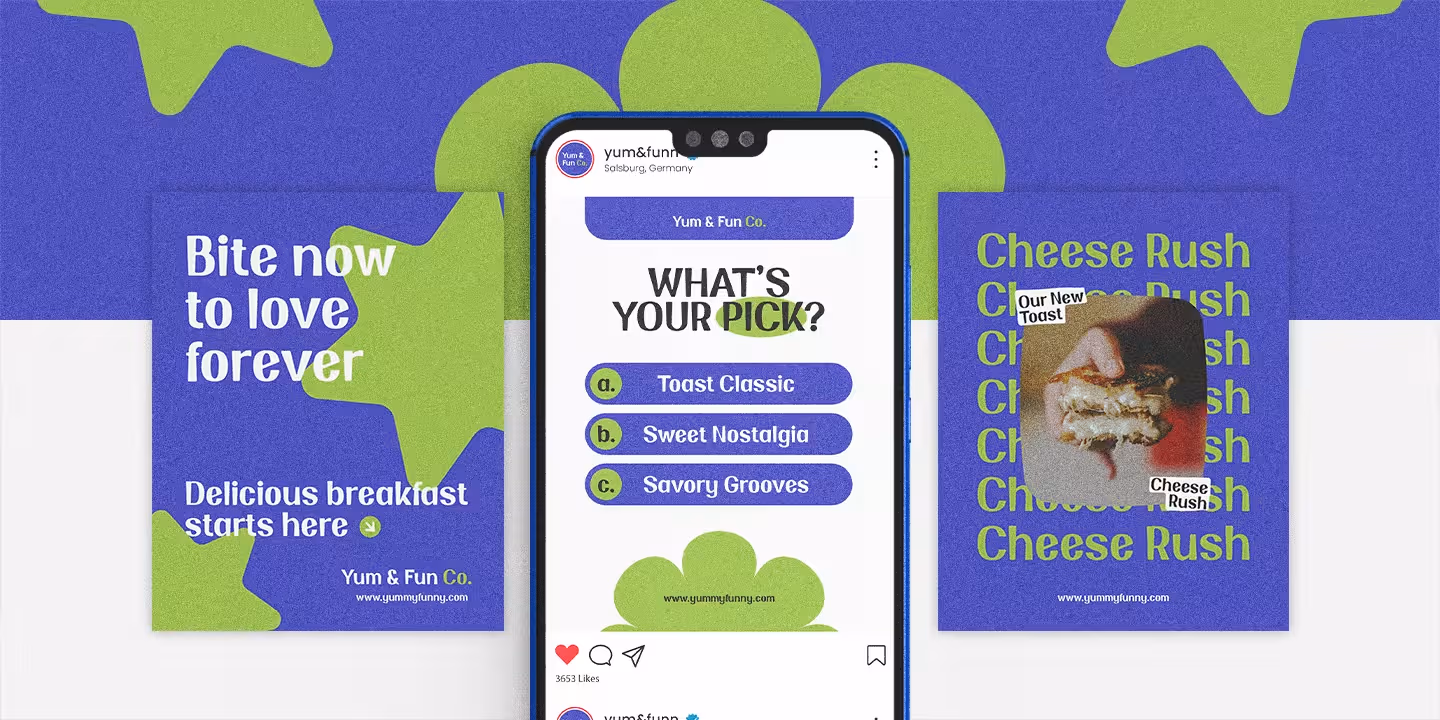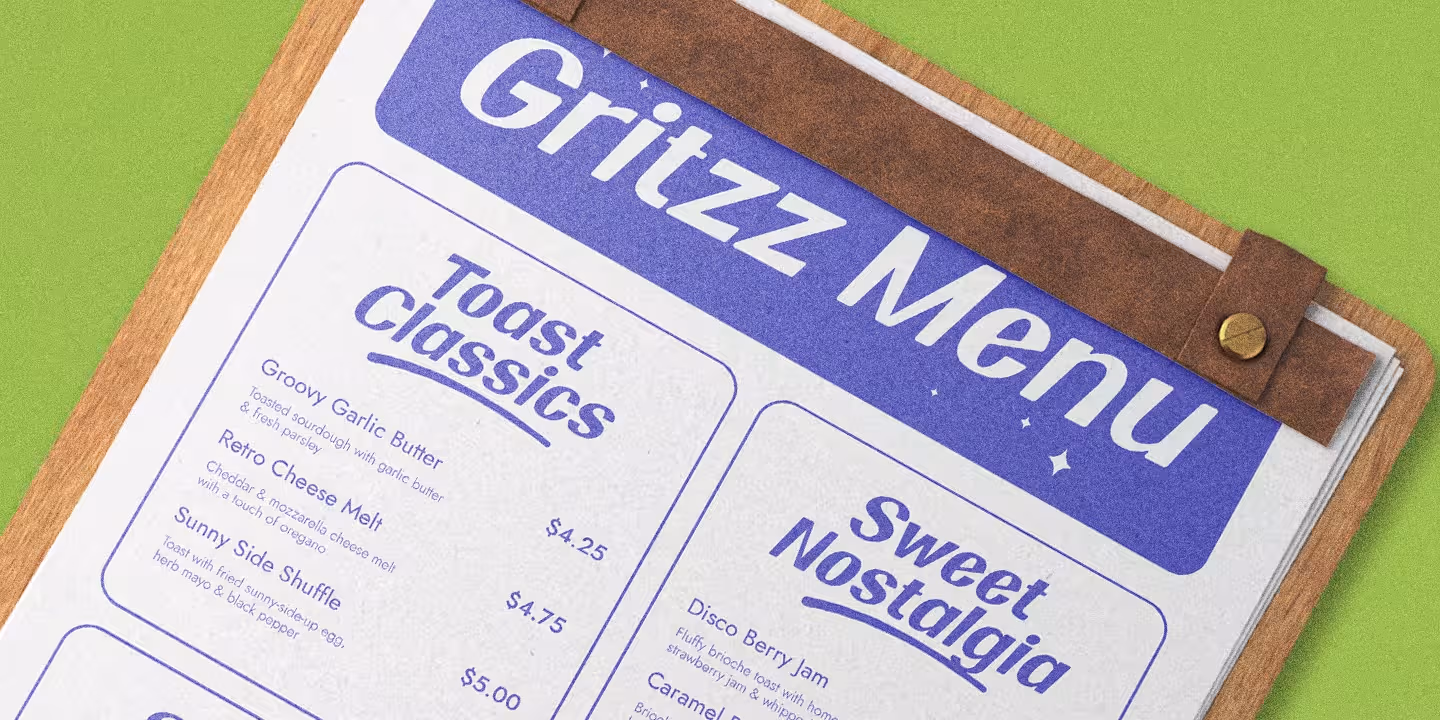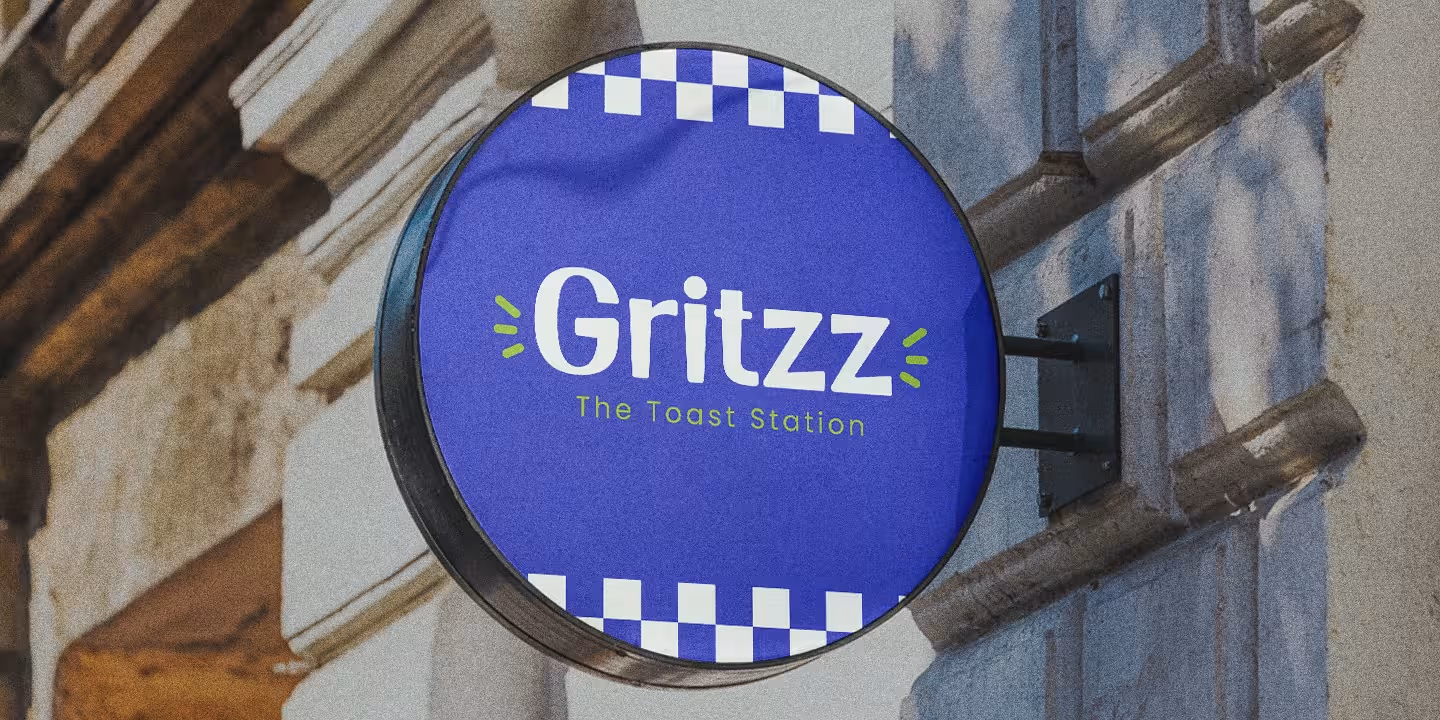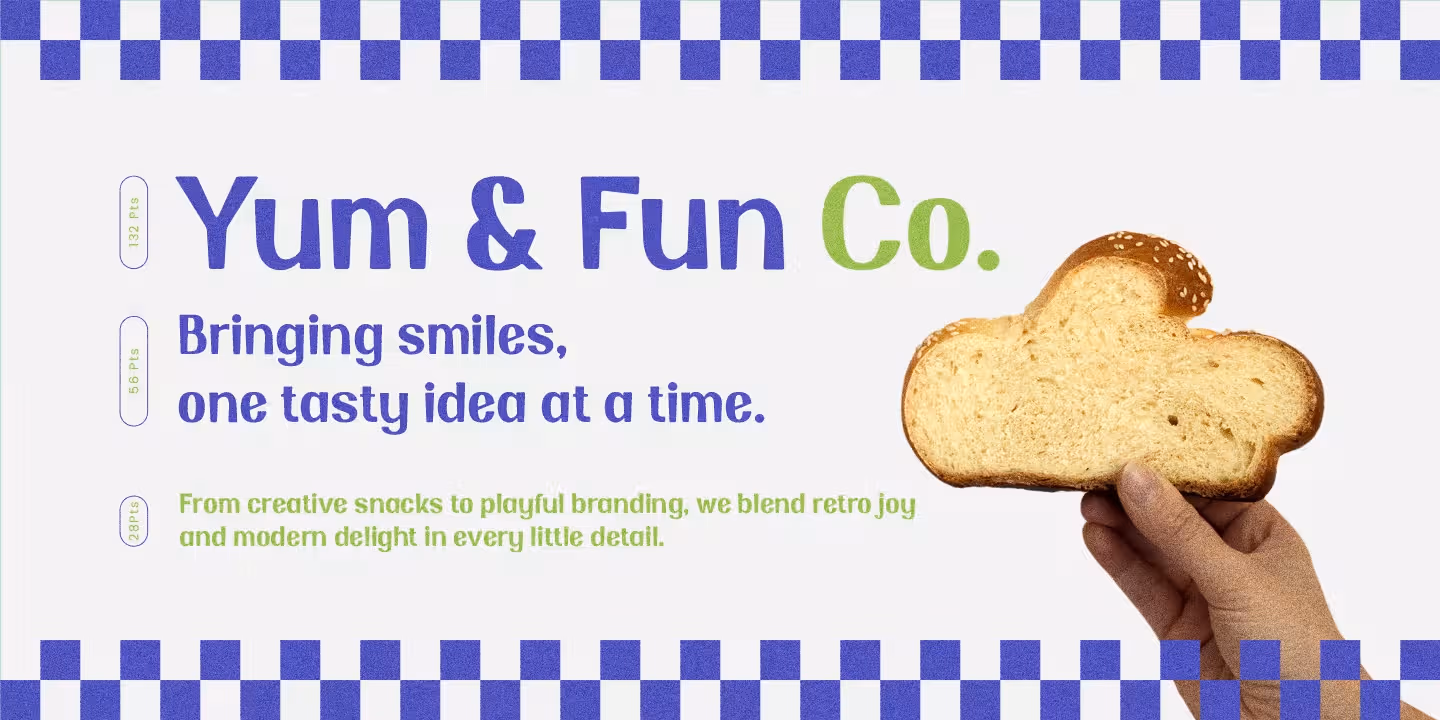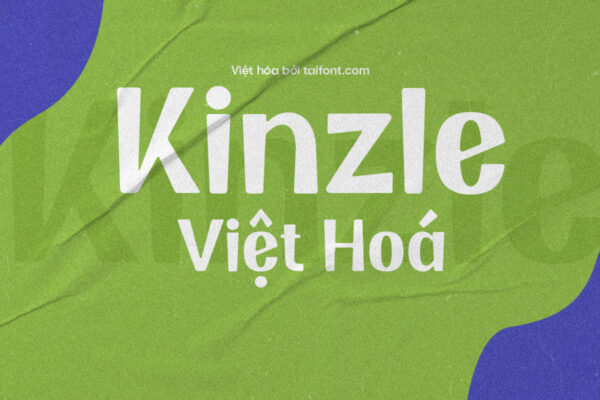
Giới thiệu về Font TF Kinzle Việt hóa
TF Kinzle Việt hóa là một font chữ không chân (sans-serif) trang trí nổi bật với vẻ đẹp độc đáo, sáng tạo và đầy cuốn hút. Font này thường mang những nét đặc trưng, đôi khi có những chi tiết phá cách nhẹ nhàng, tạo cảm giác về sự hiện đại, tinh tế nhưng vẫn rất nghệ thuật, lý tưởng để làm nổi bật các thông điệp.
Với sự sáng tạo trong thiết kế và khả năng gây ấn tượng mạnh, Kinzle là lựa chọn lý tưởng cho các ấn phẩm trong ngành ẩm thực và truyền thông xã hội:
- Thiết kế ẩm thực: Hoàn hảo để sử dụng trên menu món ăn, bảng giá, hoặc các biển hiệu của nhà hàng, quán cà phê. Font này giúp menu trở nên hấp dẫn, phong cách và dễ đọc, làm nổi bật tên món ăn và giá cả. được thiết kế tinh tế của font sẽ truyền tải cảm giác về chất lượng và sự độc đáo của ẩm thực.
- Menu món ăn: Lý tưởng cho việc trình bày các món đặc trưng, signature dishes. Nét độc đáo của font sẽ làm cho tên món ăn trở nên nổi bật và hấp dẫn, khiến khách hàng muốn khám phá.
- Poster Social Media: Phù hợp cho các poster, banner, hoặc bài đăng trên mạng xã hội quảng bá món ăn mới, chương trình khuyến mãi, hoặc các sự kiện ẩm thực. Font này sẽ giúp bài đăng của bạn thu hút sự chú ý, tạo dấu ấn riêng và dễ dàng gây ấn tượng với người xem.
Với TF Kinzle Việt hóa, bạn có thể dễ dàng thổi hồn nghệ thuật, sự tinh tế và độc đáo vào các thiết kế ẩm thực cũng như truyền thông xã hội, tạo ra những sản phẩm không chỉ đẹp mắt mà còn đầy cảm xúc và sức hút đặc biệt.
Font Việt hóa TF Kinzle